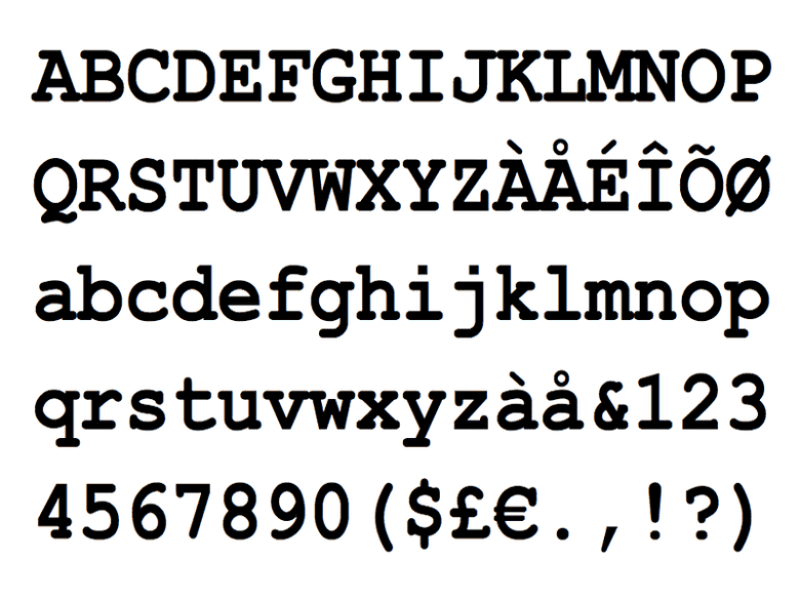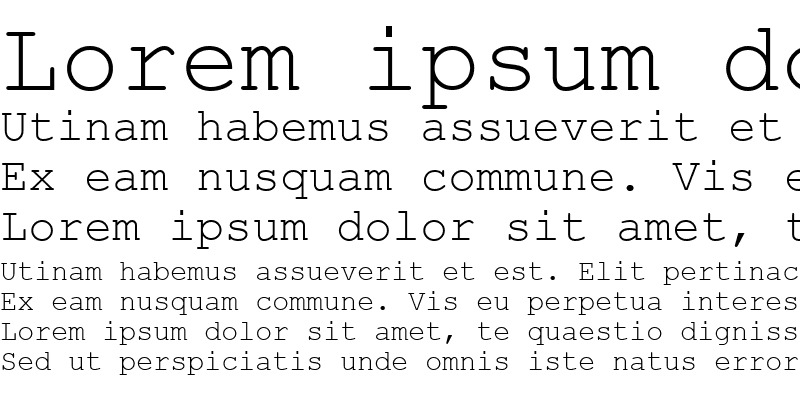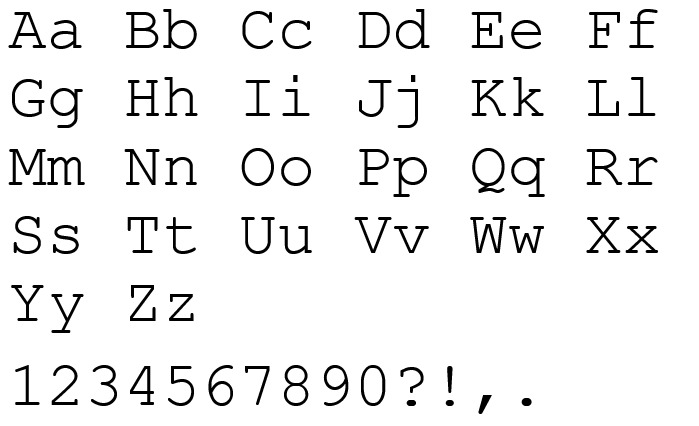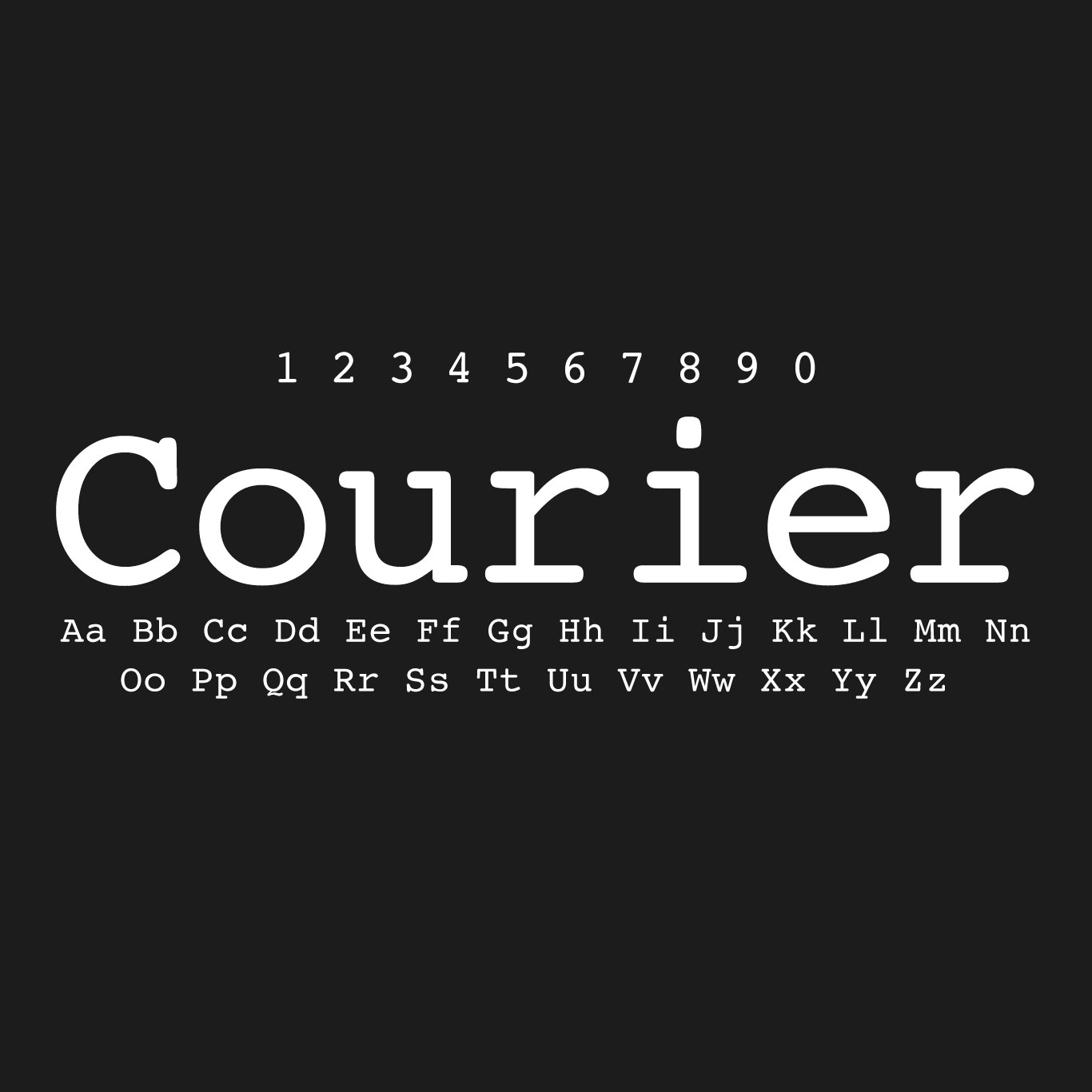
Font Courier New Việt hóa là bộ phông chữ thuộc dòng Monospaced (đơn cách) mô phỏng lại hoàn hảo kiểu chữ của những chiếc máy đánh chữ cơ học cổ điển. Được thiết kế ban đầu bởi Howard Kettler cho tập đoàn IBM và sau đó trở thành phông chữ hệ thống quen thuộc trên toàn cầu, Courier New mang lại cảm giác mộc mạc, hoài niệm và đậm chất kỹ thuật. Doozypack.vn cung cấp link tải Font Courier New Việt hóa chuẩn kỹ thuật, giúp bạn sở hữu phông chữ máy đánh chữ độc đáo này mà không lo gặp bất kỳ lỗi hiển thị dấu thanh nào khi thiết kế in ấn và soạn thảo văn bản.
Đặc điểm thẩm mỹ độc đáo của bộ font Courier New
Courier New không đi theo các chuẩn mực tỷ lệ chữ thông thường; sức hút của nó nằm ở tính kỷ luật cơ học và vẻ đẹp hoài cổ đầy hoài niệm.
Mẫu chữ Courier New
Phong cách Monospaced (Đơn cách) mô phỏng máy đánh chữ cổ điển
Đặc trưng lớn nhất của phông chữ Courier New là mọi ký tự đều chiếm một khoảng không gian chiều ngang hoàn toàn bằng nhau (fixed-width). Dù là chữ ‘i’ mảnh mai hay chữ ‘m’ rộng bản, tất cả đều nằm gọn trong các ô lưới đều đặn. Cấu trúc này mô phỏng chân thực bản in từ những chiếc máy đánh chữ thập niên 1950, tạo nên cảm giác thô mộc, chân thành và rất có chiều sâu lịch sử khi ứng dụng vào thiết kế bao bì sản phẩm.
Cấu trúc chữ thẳng thắn mang đậm dấu ấn hoài cổ
Các ký tự của Courier New Font Việt hóa sở hữu các đường nét có chân (serif) vuông vức và thẳng tắp. Sự cứng nhắc mang tính cơ học này lại vô tình trở thành điểm nhấn nghệ thuật độc đáo, giúp các bức thư tay giả lập, nhãn dán bưu phẩm hoặc các thông điệp hoài niệm trên bao bì trở nên cực kỳ có hồn và chạm đến cảm xúc người xem.
Ưu điểm nổi bật của bản phông chữ Courier New Việt hóa
Khi ứng dụng các phông chữ đơn cách quốc tế vào thị trường trong nước, sự chỉn chu về dấu câu là yếu tố quyết định đến tính chuyên nghiệp của ấn phẩm:
• Khắc phục triệt để lỗi dấu tiếng Việt: Phiên bản Việt hóa đã được đội ngũ thiết kế trau chuốt thủ công từng dấu câu. Các dấu sắc, huyền, hỏi, ngã, nặng được vẽ đồng điệu với cấu trúc đơn cách của thân chữ, không gây cảm giác chắp vá hay va chạm vào các ký tự đứng liền kề.
Kiểu chữ monospace rõ nét
• Bao bì Cà phê rang mộc & Trà truyền thống: Tiêu đề và bảng thành phần in bằng font Courier New kết hợp cùng chất liệu giấy Kraft nâu tạo nên phong cách Vintage nguyên bản.
• Tem nhãn mã vạch & Lô sản xuất (Batch Code): Cấu trúc đơn cách chuẩn xác rất phù hợp để in ấn các dãy số serial, ngày sản xuất trên tem decal dán bao bì công nghiệp.
Thiết kế typography cổ điển
Lưu ý kỹ thuật khi in ấn với phông chữ máy đánh chữ Courier New
Việc sản xuất bao bì thực tế sử dụng các phông chữ cơ học đòi hỏi sự am hiểu kỹ thuật chuyên sâu tại xưởng in Doozypack.vn:
• Kiểm soát hiện tượng tràn mực (Dot Gain): Các nét chữ của Courier New có độ dày vừa phải nhưng cấu trúc đơn cách tạo ra nhiều khoảng trống. Trên giấy Kraft thô nhám, hãy đảm bảo size chữ tối thiểu từ 8pt trở lên để thông tin luôn rõ ràng.
• Hệ màu CMYK chuẩn cho văn bản nhỏ: Luôn thiết kế trên hệ màu CMYK và đặt màu đen cho văn bản ở thông số K=100 đơn sắc để chữ sắc nét nhất, tránh hiện tượng nhòe màu khi in Offset.
• Quy tắc Convert Font bắt buộc: Trước khi gửi file in PDF cuối cùng đến Doozypack.vn, hãy luôn thực hiện lệnh Create Outlines (Ctrl+Shift+O) cho toàn bộ văn bản để tránh tình trạng máy in của xưởng bị thiếu font gây lỗi nhảy chữ.